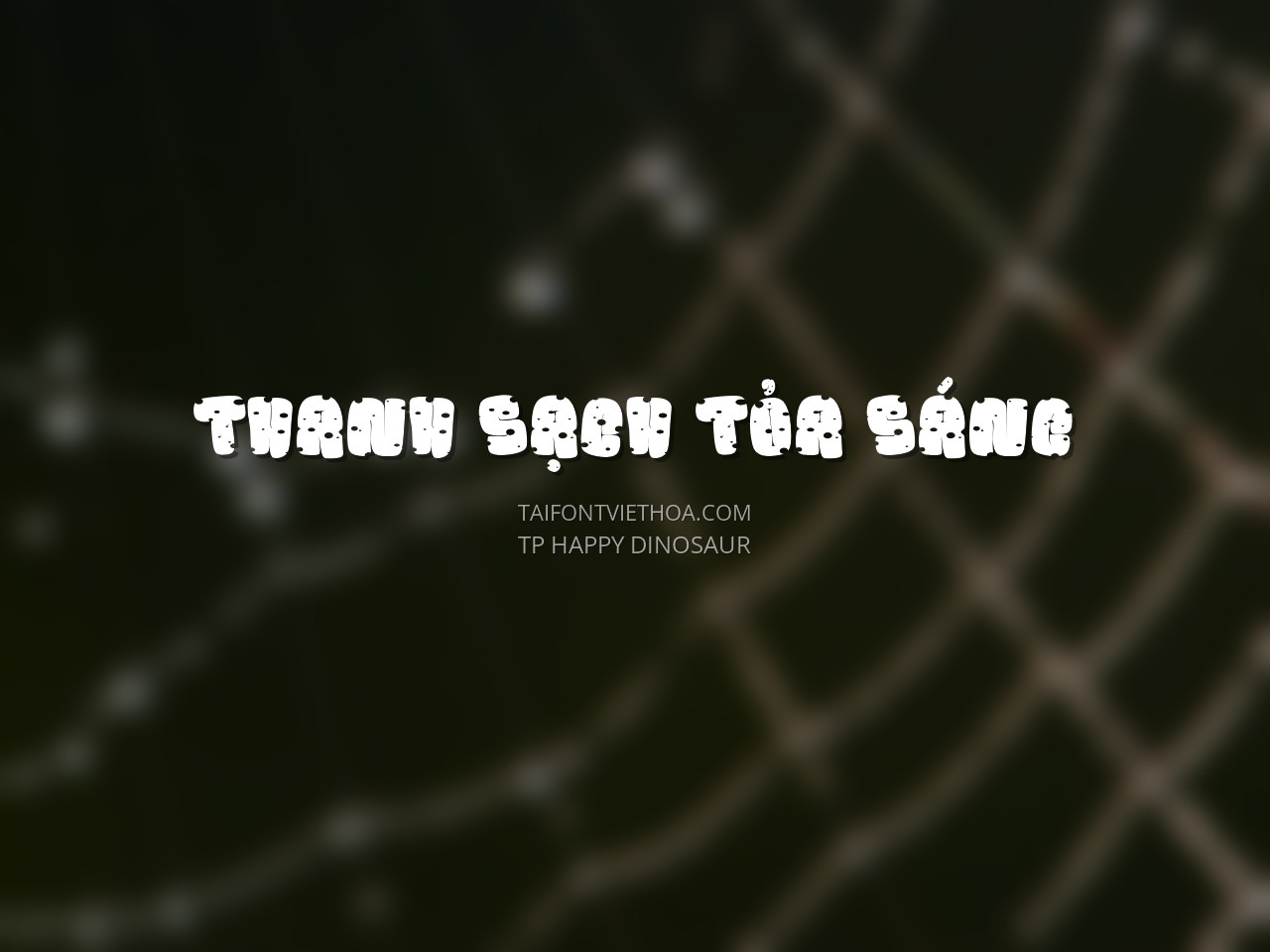
Font việt hóa TP Happy Dinosaur
Tác giả Font: Sipanji
Giới thiệu về font TP Happy Dinosaur – Kiểu chữ decorative vui nhộn, thân thiện và đáng yêu
TP Happy Dinosaur là phiên bản Việt hóa của font Happy Dinosaur – một kiểu chữ decorative mang phong cách vui nhộn, thân thiện và rất đáng yêu. Font được thiết kế với các nét chữ mềm mại, tròn trịa và sinh động, phù hợp cho các dự án thiết kế poster, bao bì, thiệp mời và các sản phẩm dành cho trẻ em.
Thiết kế decorative thân thiện – Lý tưởng cho dự án dành cho trẻ em và gia đình
TP Happy Dinosaur sở hữu các nét chữ tròn trịa, mềm mại và vui tươi, tạo cảm giác thân thiện, gần gũi và sinh động. Font rất phù hợp cho tiêu đề, poster, bao bì sản phẩm hoặc các phần thiết kế cần sự nổi bật và dễ thương. Phong cách thiết kế của Happy Dinosaur rất thích hợp với các dự án giáo dục, đồ chơi trẻ em, quà tặng và truyền thông gia đình.
Ứng dụng lý tưởng: thiết kế poster, thiệp mời, bao bì sản phẩm, bài đăng mạng xã hội và các dự án sáng tạo cần phong cách vui tươi, thân thiện. Ngành nghề phù hợp: giáo dục, đồ chơi trẻ em, quà tặng, truyền thông gia đình và các thương hiệu định vị theo phong cách đáng yêu, thân thiện.